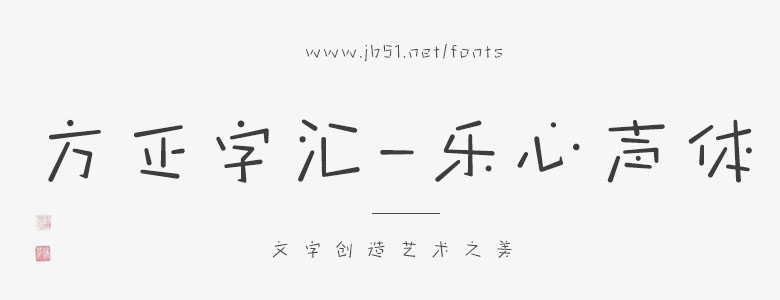
方正字匯-樂(lè)心聲體是一款創(chuàng)意卡通字體,在字體中能感受到孩子般的樂(lè)趣,調(diào)皮中又不失穩(wěn)重,字形略長(zhǎng),一筆一劃猶如一根根胖乎乎的小手指,粗壯穩(wěn)定且動(dòng)感十足,看似毫無(wú)章法,但組合起來(lái)無(wú)一絲違和感,筆畫(huà)時(shí)細(xì)時(shí)粗,變化明顯,對(duì)比強(qiáng)烈,彰顯活潑生動(dòng)的氣質(zhì),用圓形筆劃演繹來(lái)顯示孩子不拘一格的心態(tài),充滿歡樂(lè)心聲處處聞的感受,是一款適用于兒童品牌的時(shí)尚字體。